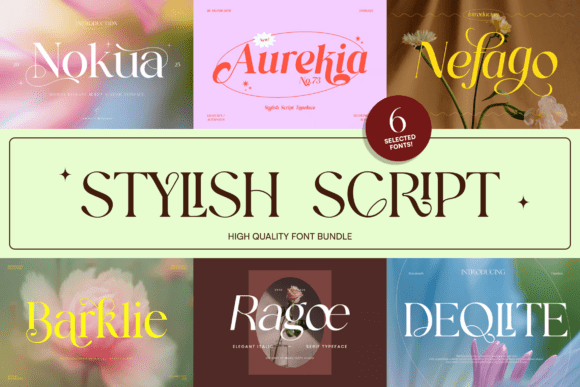
Stylish Script Bundle
Mencari elemen desain yang tepat bisa jadi sulit, namun Stylish Script Bundle menawarkan koleksi luar biasa yang akan langsung meningkatkan kualitas karya Anda.
Baik Anda membuat produk POD (Print on Demand), undangan pernikahan, atau grafis media sosial, Stylish Script Bundle adalah pilihan yang sangat ideal.